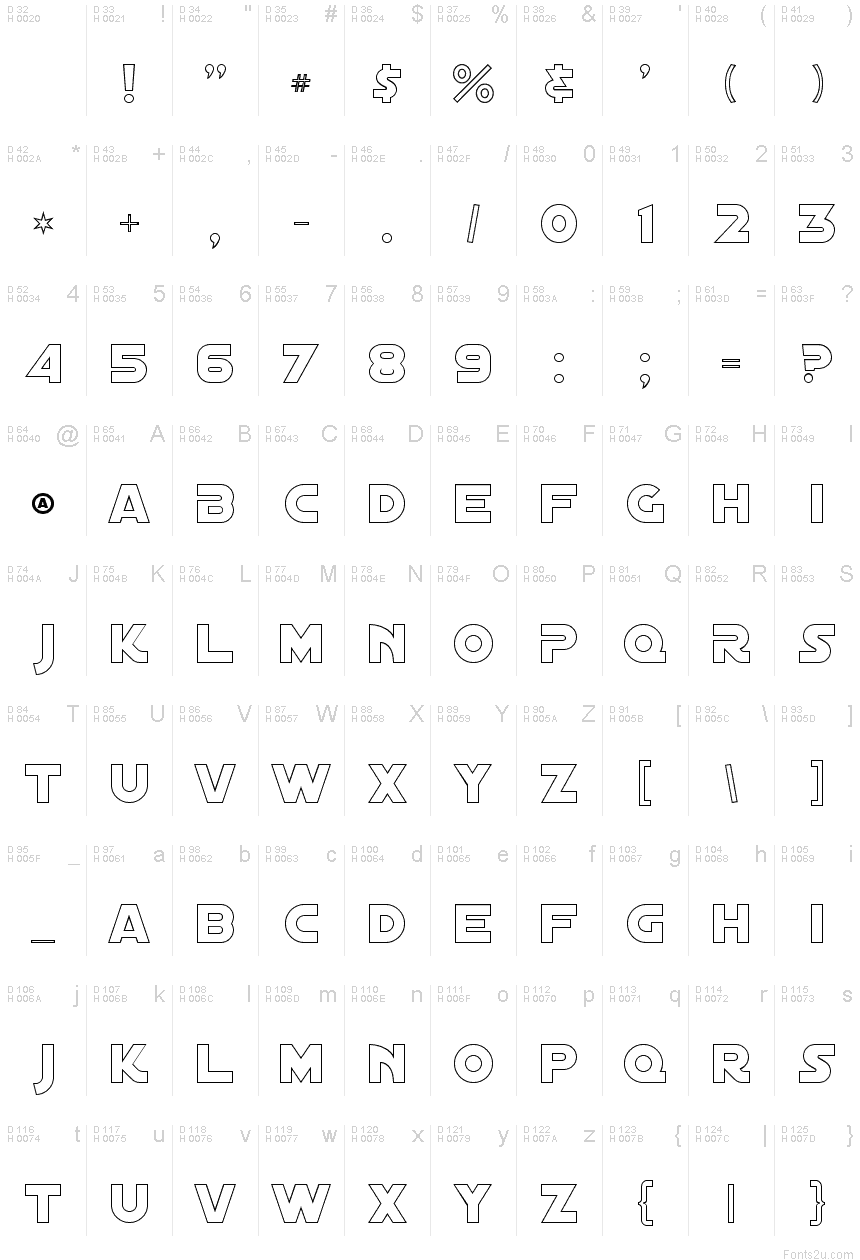
<p>Distant Galaxy Outline von ShyWedge ist eine kostenlose, futuristische Outline-Schrift, die wirkt, als wäre sie aus Neonlicht gezeichnet. Die hohen, quadratischen Formen und die weiten, gleichmäßigen Abstände verleihen jedem Buchstaben ein schwereloses, schwebendes Gefühl, während die hohlen Striche Raum für Farben, Texturen oder Leuchteffekte lassen. Sie ist kühn, filmreif und vermittelt sofort Sci-Fi-Atmosphäre, ohne überladen oder kitschig zu wirken.</p>
<p>Mit Distant Galaxy Outline rücken Titel für Filmplakate, Gaming-Logos, Sci-Fi-Buchtitel, Event-Flyer, Tech-Konferenzen und Streaming-Thumbnails sofort in den Fokus. Diese kostenlose Schrift glänzt in großen Größen, wo die klaren Konturen messerscharf bleiben; kombinieren Sie sie am besten mit einer schlichten, geometrischen serifenlosen Schrift für Fließtexte, damit die leuchtenden Buchstaben voll zur Geltung kommen.</p>
Distant Galaxy Outline